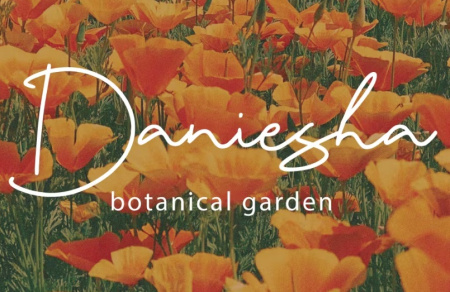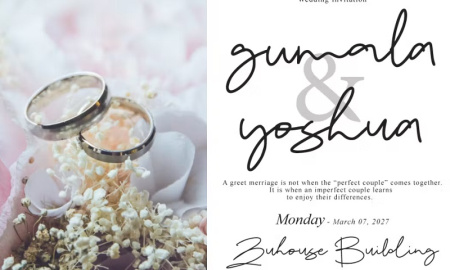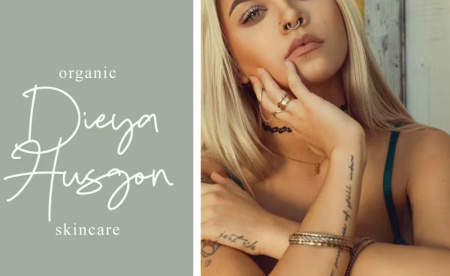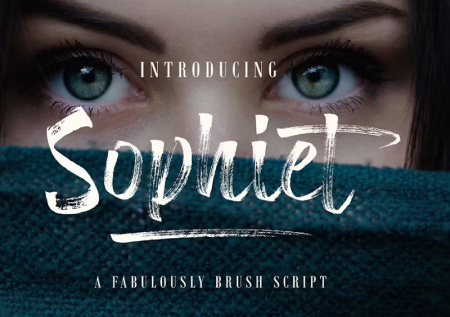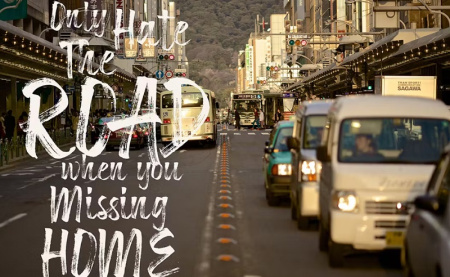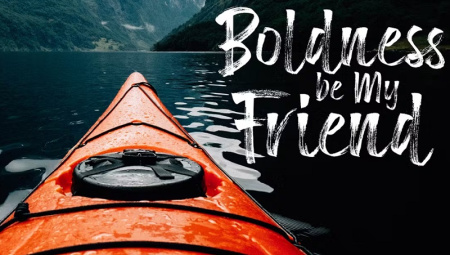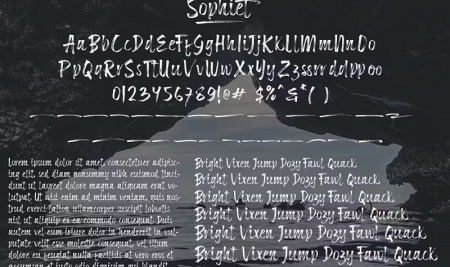
2 فونت انگلیسی چهره زیبا
فونت انگلیسی چهره
فونت انگلیسی چهره شامل 2 فونت زیبا است که جدیدترین فونت برای طراحی چهره می باشد. فونت چهره انگلیسی برای طراحی هایی مانند کارت تبریک، مواد نام تجاری، کارت ویزیت، نقل قول، پوستر، و غیره مناسب است. در ادامه با مشاهده تصاویر این فونت زیبا با ما همراه باشید.
✅ نام فونت انگلیسی1: Sophiet
✅ نام فونت انگلیسی2: Lindgen
✅ حروف بزرگ و کوچک بین‌المللی زبان و نمادها از علامت‌گذاری و شماره پشتیبانی می‌کنند.